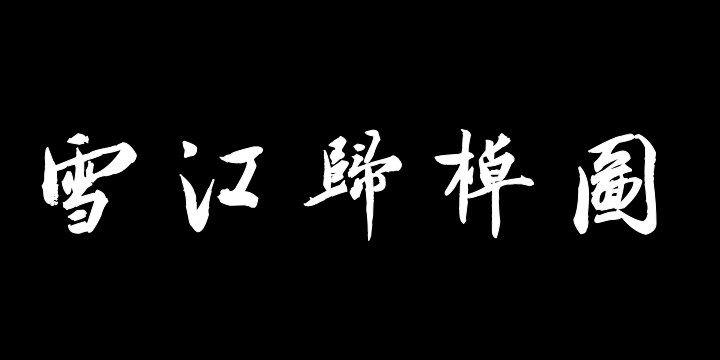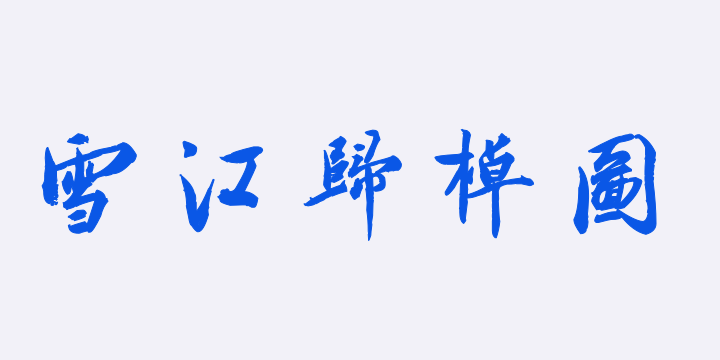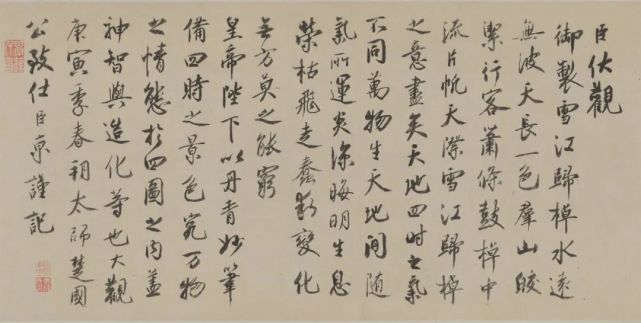
字体全名: 汉标蔡京题跋雪江归棹图卷
铸字厂: 真迹小字库
字体简介: 下载须知:本字库非标准GB2312字库。本字库只包含了蔡京行书题跋《雪江归棹图卷》真迹上的“155个字”。详见图样。此帖为蔡京行书题跋《雪江归棹图卷》,现藏于北京故宫博物院。《雪江归棹图卷》为赵佶即宋徽宗绘寒江两岸的雪景,极富层层深入、峰回路转之情趣。是一幅描绘冬日雪景的山水画。而蔡京书法造诣颇深,其书法艺术有姿媚豪健、痛快沉着的特点,能体现宋代“尚意”的书法美学情趣。